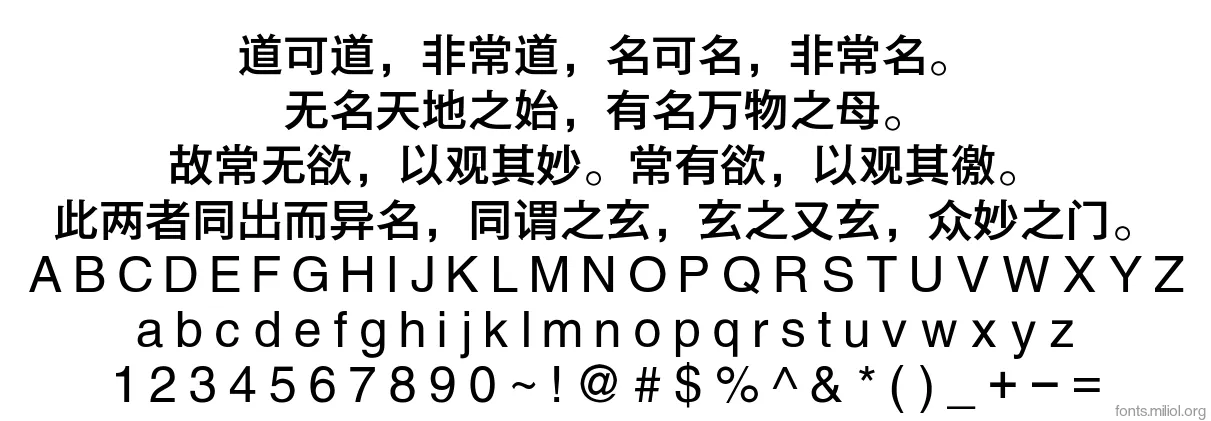
《方正韵动中黑_GBK:现代设计中的经典字体选择》
方正韵动中黑_GBK(FZYunDongHei-M-GBK)是一款兼具力量感与流畅性的黑体字体,由方正字库精心设计。其笔画粗细均匀,结构稳重而不失灵动,既适合标题设计,也能胜任正文排版,尤其在中文字体应用中展现出优秀的可读性。GBK编码的支持使其能够覆盖绝大多数汉字字符,满足多场景需求。
这款字体融合了传统黑体的严谨与现代设计的简洁,视觉上干净利落,适用于品牌标识、广告宣传、数字媒体等多种设计领域。无论是印刷品还是屏幕显示,方正韵动中黑_GBK都能保持清晰的呈现效果,为设计作品增添专业气质。
作为一款经典字体,方正韵动中黑_GBK凭借其平衡的美学特征和实用性,成为设计师常用的工具之一,值得在设计项目中尝试应用。